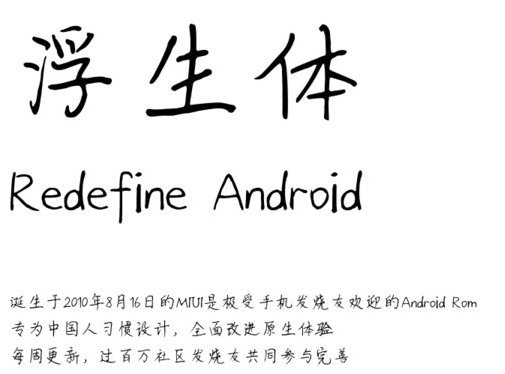
浮生體筆畫恣意而灑脫,給你不拘泥與框架舒服的自在感,筆畫清晰可認(rèn),下筆純粹而有神,便于讀者讀取和欣賞,喜歡的朋友就來(lái)綠色資源網(wǎng)體驗(yàn)吧!
一筆一紙一傾塵,一生一世一雙人; 一悲一喜一浮生,一醉一醒一游人。
浮生體字體是一款適合鋼筆書法書寫的字體,有著極其精簡(jiǎn)的線條和后現(xiàn)代的設(shè)計(jì)美感,讓文字更加質(zhì)樸大方,讓你的包裝設(shè)計(jì)、廣告策略更吸引人!